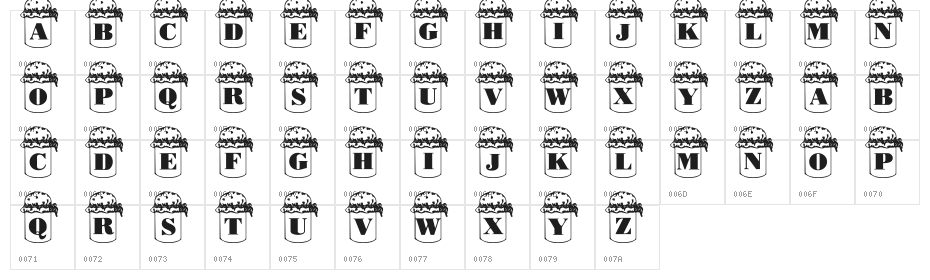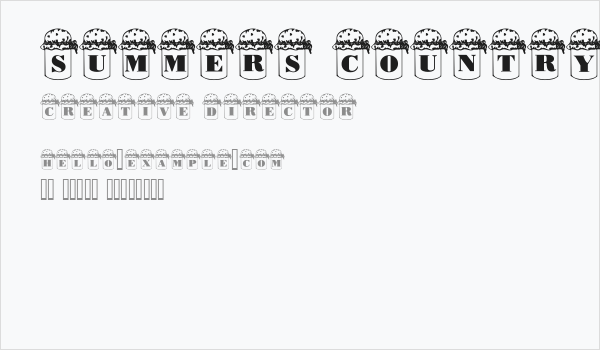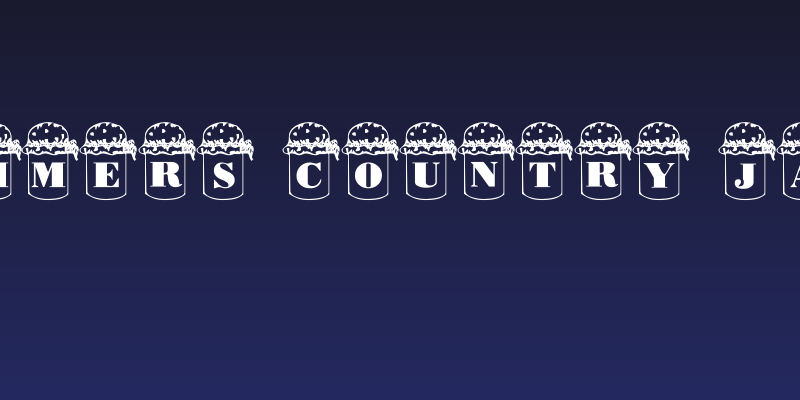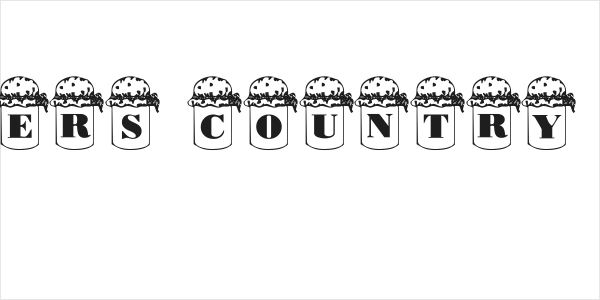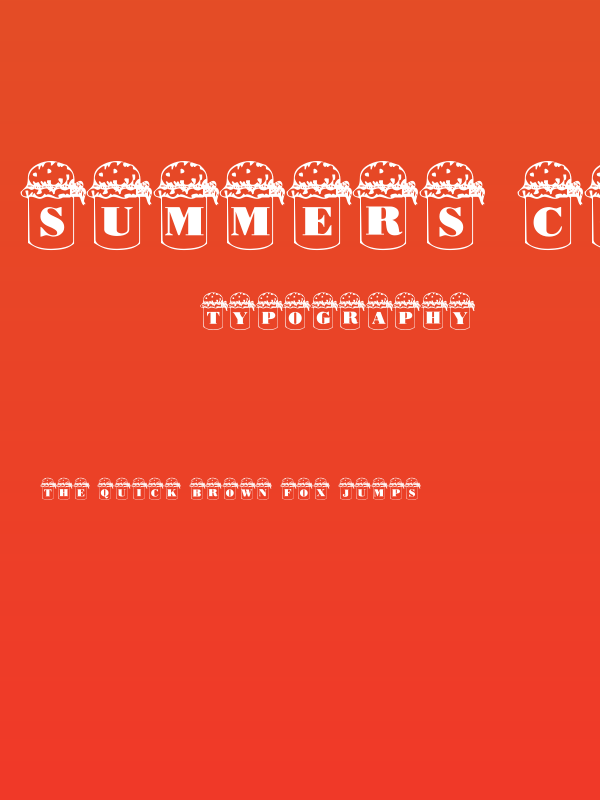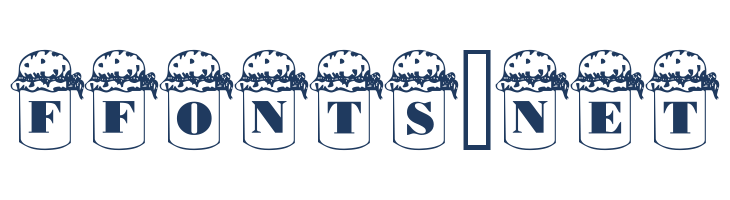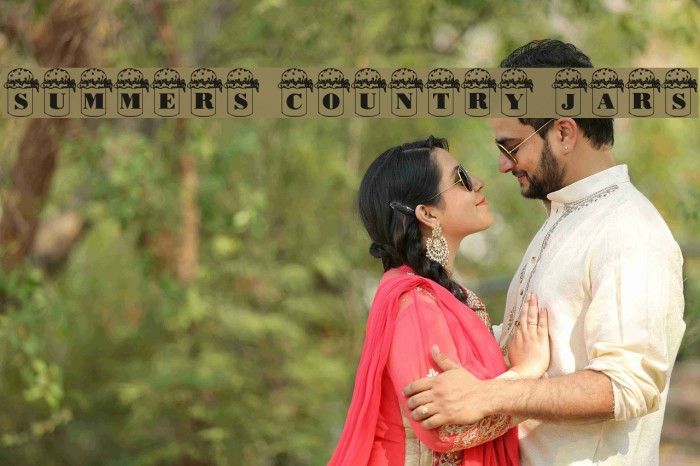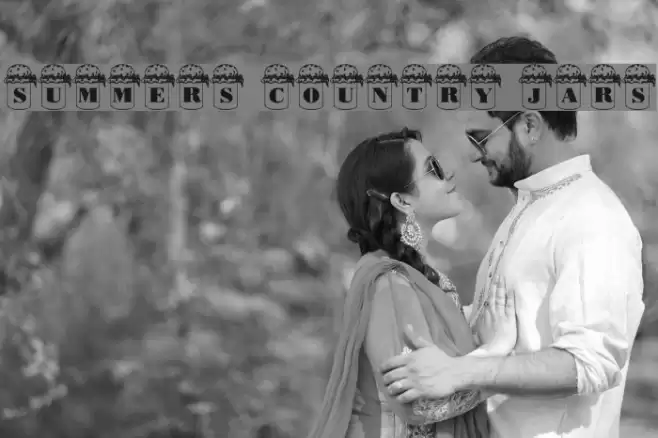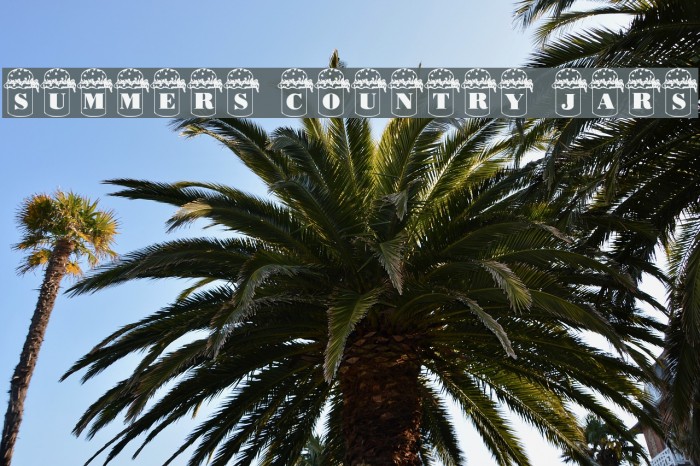
Summers Country Jars Font
| الاسم | Summers Country Jars |
| الفئات | Images & Symbols |
| حالة الاستخدام | Headlines, Logos, Themed Designs |
| مشاريع مقترحة | Ideal for craft labels, children's book titles, kitchen decor, and themed event invitations. |